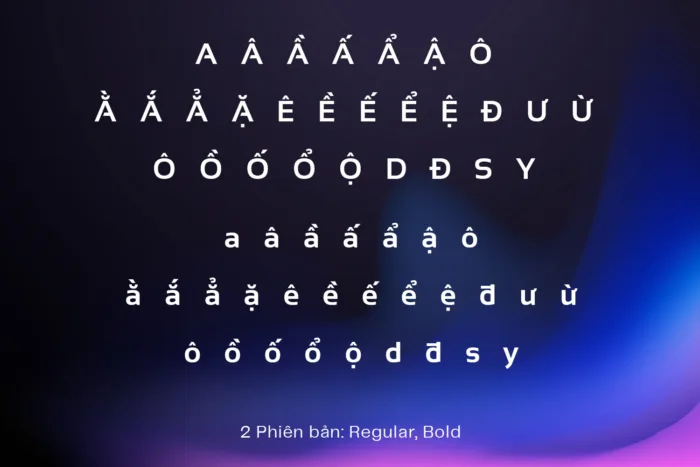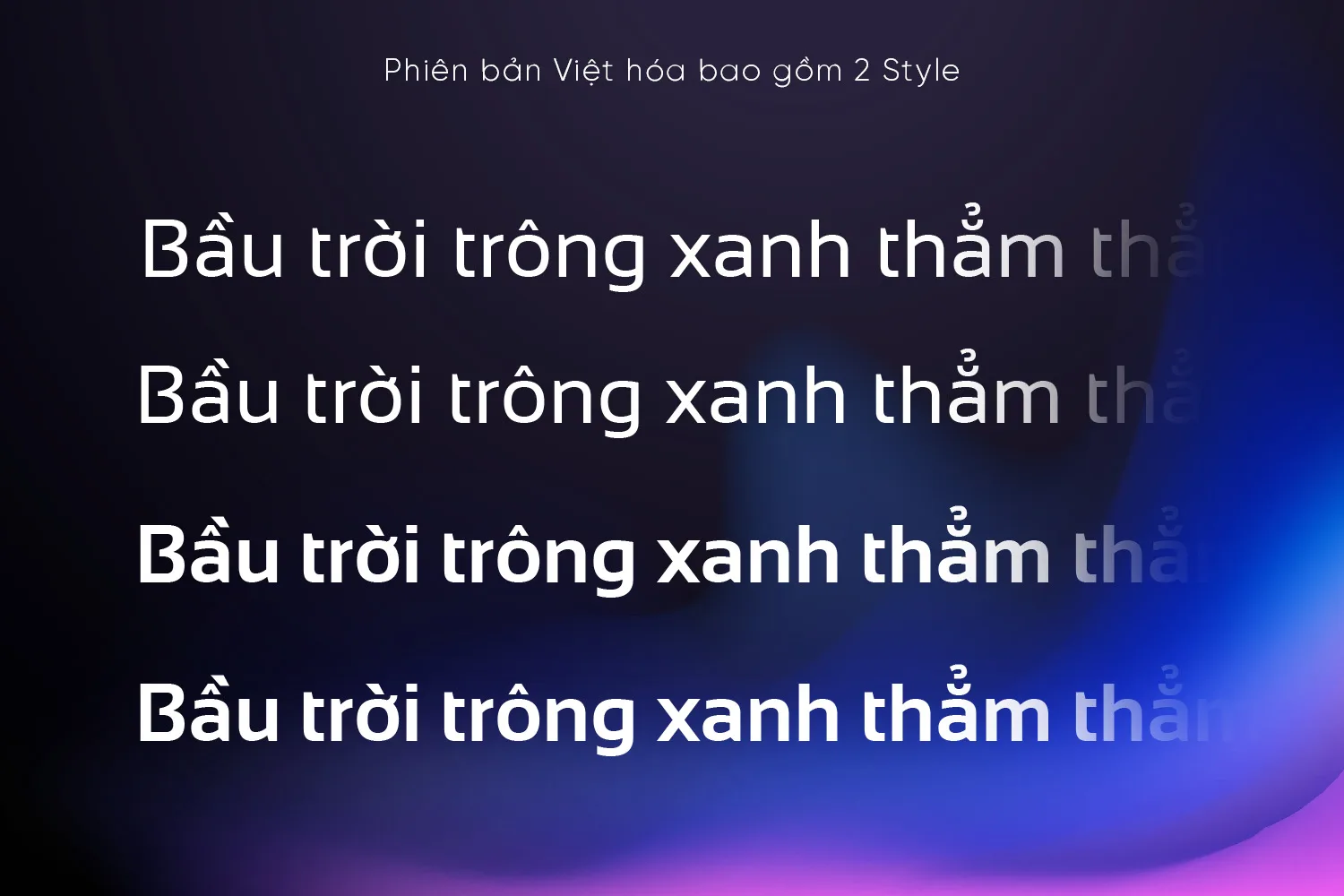
DVN Sansation Việt hóa – Font chữ không chân thân thiện và hiện đại (2 Style)
DVN Sansation là phiên bản Việt hóa của font Sansation do Bernd Montag thiết kế, mang đến một kiểu chữ sans-serif nhẹ nhàng, hiện đại và dễ tiếp cận. Font nổi bật với các đường cong uyển chuyển, thân chữ tròn đều và độ mở thoáng, tạo cảm giác mềm mại, dễ đọc trong cả văn bản dài lẫn tiêu đề ngắn. Phong cách thiết kế của DVN Sansation cân bằng giữa tính công nghệ và cảm xúc, rất phù hợp cho các dự án web, giao diện ứng dụng, thiết kế nhận diện thương hiệu hoặc ấn phẩm truyền thông số. Bộ font hỗ trợ đầy đủ tiếng Việt, giữ nguyên vẻ hài hòa trong cách đặt dấu và cấu trúc chữ. Nhẹ nhàng nhưng không đơn điệu, DVN Sansation là lựa chọn lý tưởng cho những ai tìm kiếm một phông chữ hiện đại, thân thiện và linh hoạt trong nhiều bối cảnh thiết kế.
Phiên bản Việt hóa bao gồm 2 Style: Regular, Bold